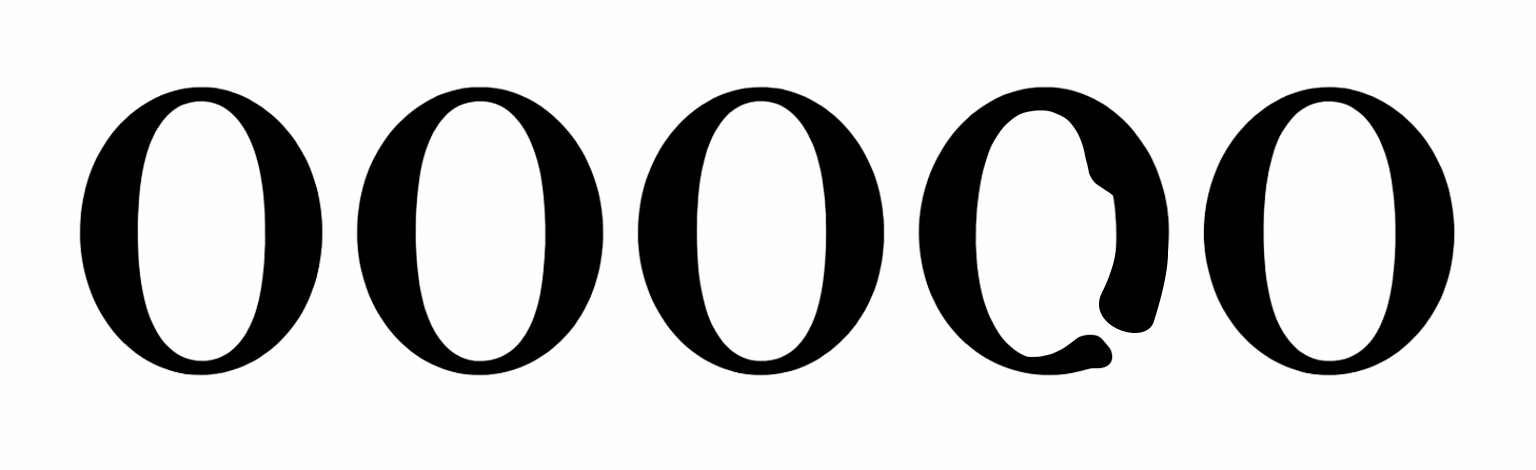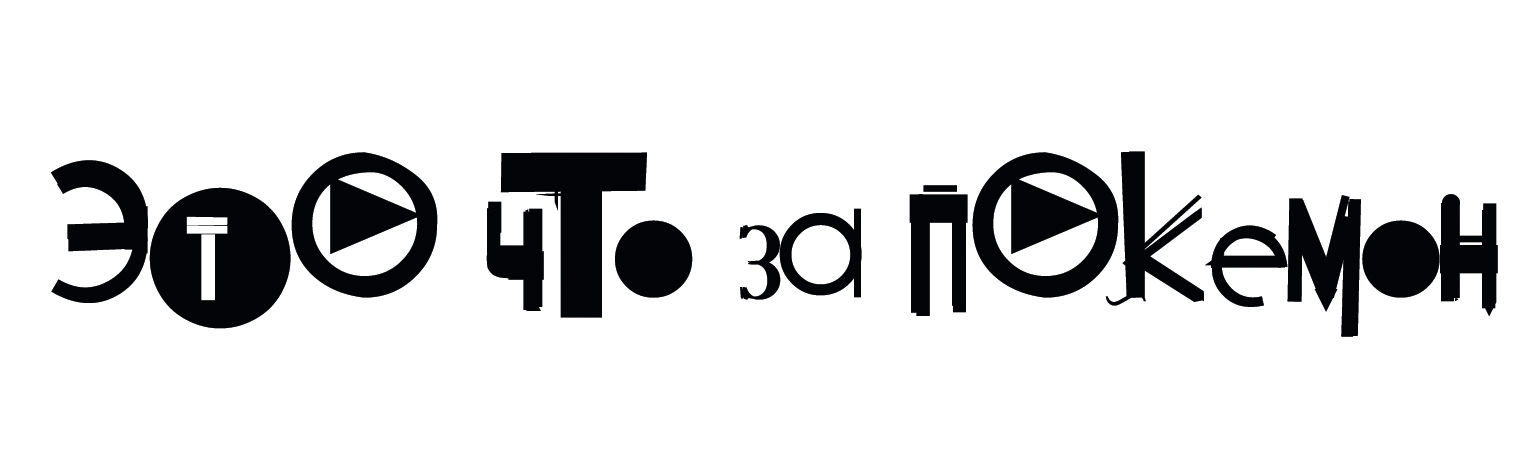
Генеративный шрифт и нейросети: современное состояние, типология особенностей и перспективы стиля
Развитие генеративных нейросетей открыло новые возможности для создания изображений, включая тексты и буквы, без участия человека. Уже давно не секрет, что современные дизайнеры могут с помощью текстовых описаний получать «нейро-изображения» – от ии-фото до художественных иллюстраций и даже видео, – и часто такие изображения содержат текстовые элементы. Генеративный шрифт (Generative Font) — это тип шрифта, форма и стиль глифов которого создаются не вручную дизайнером «буква за буквой», а с помощью программного кода, алгоритмов или искусственного интеллекта. Строго говоря, шрифтом это называть нельзя. Это скорее «нейро-текст», визуальный почерк эпохи искусственного интеллекта: AI-модели воспроизводят буквы, но делают это не так, как традиционные шрифтовые программы или люди. Вместо аккуратных системных литер нейросети порой выдают искажённые надписи – с лишними штрихами, гибридными формами или совсем нечитабельный «шрифт» из абстрактных символов.
Тем не менее эти же ошибки и артефакты постепенно становятся дизайнерским ресурсом и инструментом для достижения различных коммуникационных целей, а чаще просто принимаются из-за нехватки бюджета или времени на доработку дизайн-макета. Цель данной статьи – исследовать, как нейросети генерируют буквы, какие специфические закономерности и артефакты при этом возникают, и как эти особенности могут быть осмысленно использованы дизайнерами. Также мы рассмотрим, понимают ли современные модели принципы шрифтов (строение графем, различие между латиницей и кириллицей и т.д.), и обсудим перспективы улучшения качества генерации текста: смогут ли нейросети в будущем создавать идеальные буквы без характерных искажений.
Генерация изображений с текстом: от первых моделей к современным
Создание осмысленного текста – одна из самых сложных задач для генеративных моделей изображений. Ранние системы вроде DALL-E, Stable Diffusion, Midjourney и др. применяли нейросетевые диффузионные модели для превращения текстового описания в картинку. Однако точное воспроизведение букв никогда не было их сильной стороной. Модели обучения ориентировались прежде всего на реалистичность и общую композицию изображения, поэтому текст воспринимался ими лишь как часть визуального шума или орнамента и узора, а не как знаковая система. Соответственно, попытки сгенерировать осмысленную надпись зачастую приводили к бессмысленному набору линий, отдалённо напоминающих буквы. Например, ранние версии Midjourney фокусировались на визуальных элементах и не уделяли внимания буквам – поэтому текст выходил как «бессмысленные каракули» вместо осмысленных слов.
Midjourney Output
Изображение, сгенерированное ранней версией Midjourney по промпту «generate a birthday card with the phrase 'Happy Birthday, Alex!' prominently displayed», Источник
Эта проблема во многом объясняется ограничениями обучающих данных: стандартные наборы изображений содержат относительно мало примеров чётко представленного текста (например, фото с чисто напечатанными надписями), поэтому модель просто не научилась писать разборчиво. В результате даже простое слово, запрошенное в prompt, могло превратиться в нечитаемый набор символов.
Почему же нейросети так трудятся над буквами? Дело в том, что генеративная модель не обладает врождённым пониманием алфавита – она оперирует статистическими образами. В отличие от человека, который знает, что слово состоит из определённых последовательных знаков, диффузионная сеть видит текст как картинку, как набор форм, а не как семантические символы. Малейшее искажение формы буквы, совершенно терпимое для объекта вроде пейзажа или животного, для текста оказывается фатальным: смещение черты или лишний изгиб делают букву неузнаваемой для нашего глаза.
Исследователи отмечают, что нейросети воспринимают буквы как визуальные текстуры, а не как знаки со строгими правилами, поэтому даже небольшое отклонение (например, слипшиеся или наложенные буквы, отсутствующая засечка) рушит читаемость слова. Человек мгновенно замечает любое отклонение от привычных очертаний букв, «спотыкается» и сталкивается с трудностями в чтении. Отсутствие буквального «понимания» текста у модели дополняется и особенностями обучения на ранних этапах: как правило, модели не обучались специально тонкостям типографики. Их задача – выдавать правдоподобную картинку в целом, а не точно соблюдать символы. Если размытая или изменённая буква не сильно портит общую эстетику изображения, модель легко «считает» такой результат приемлемым в функции потерь. У неё нет встроенной функции проверки орфографии или строгого контроля последовательности букв, как у человека. Поэтому ранние генеративные нейросети, даже обладая огромными параметрами, буквально не умели писать: вместо заданного слова «Truth» они выводили что-то вроде «Trutt» или «TURTH», стараясь лишь приблизительно воспроизвести образ слова, но не точные буквы.
Для практического дизайна такой «глючный» текст был бесполезен. Пользователям приходилось тратить время на постобработку: дорисовывать или заменять буквы вручную, что уменьшало профит от использования ИИ в подобных макетах. Таким образом, на ранних этапах генеративный текст в изображениях воспринимался скорее как раздражающий артефакт, чем как полезная функция.
Новое поколение моделей: решение «текстовой проблемы»
Ситуация начала меняться с появлением нового поколения моделей, в которых разработчики уделили особое внимание буквам. В 2023–2025 годах вышли системы, заявленные как умеющие генерировать чёткий и разборчивый текст прямо внутри изображения. К ним относятся, например, модель Gemini 3 Pro Image от Google (известная под кодовым названием Nano Banana Pro) и мультимодальные возможности GPT-4 от OpenAI (интегрированные в систему под названием Sora и GPT-4 Vision). В этих моделях нейросеть фактически совмещает навыки большой языковой модели и генератора изображений, что даёт неожиданно хороший эффект: модель знает, какие слова она должна вывести, и старается отобразить именно их. Так, OpenAI в марте 2025 года сообщала, что новая версия GPT-4 с генерацией изображений «превосходно точно воспроизводит текст», строго следуя заданным надписям. По сути, нейросеть впервые начала воспринимать текст внутри картинки не как абстрактный фон, а как семантически значимый объект, требующий точности.
Пример генерации текста в мультимодальной GPT-4o. Источник
У Google схожий подход: многомодальная система Gemini 3 способна генерировать постеры, диаграммы и даже переводы надписей на разные языки, сохраняя при этом высокую разборчивость шрифта. На официальной странице Gemini Image подчёркивается возможность «генерировать чёткий текст для плакатов… с последующим переводом дизайна под разные локализации». Ключевой упор – на резкость и читабельность букв: пользователь может описать даже тип шрифта или имитировать рукопись, и модель постарается это выполнить. Иными словами, новейшие генеративные сети начинают учитывать правила письма и формы букв, а не только общую картинку.